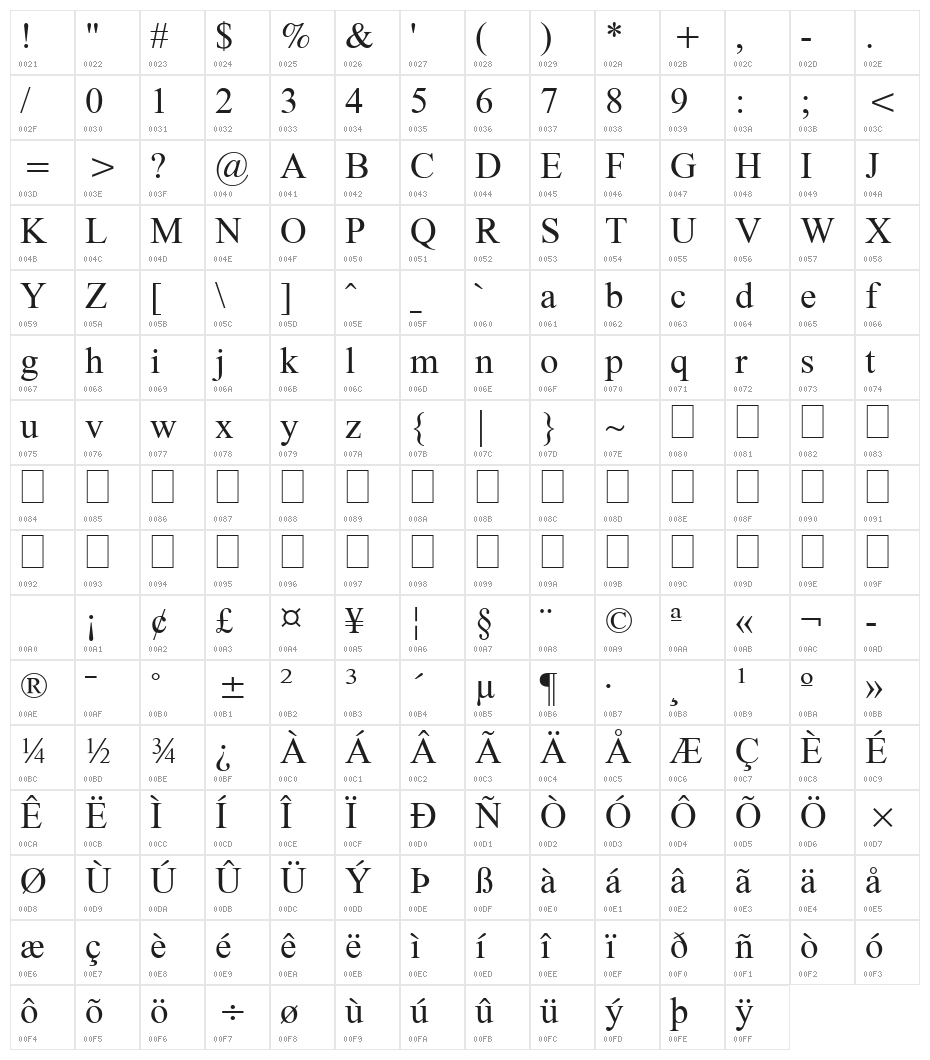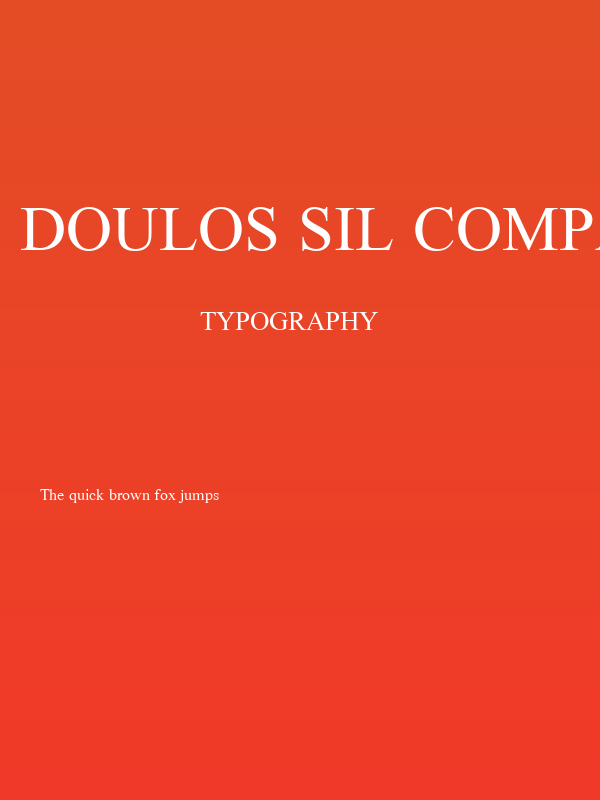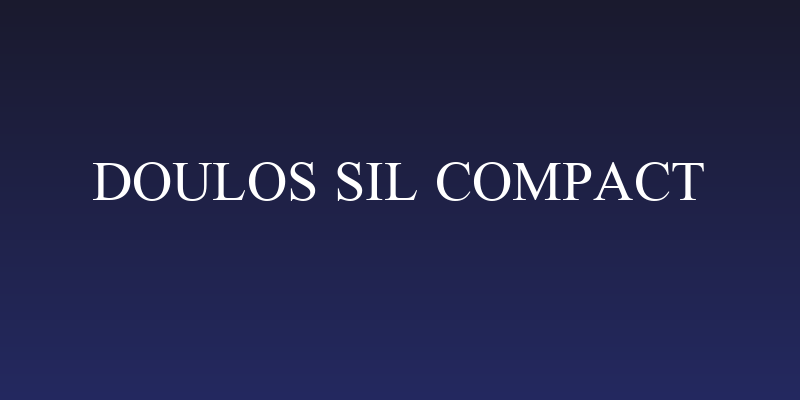
Doulos SIL Compact Font
| Nome | Doulos SIL Compact |
| Categorie | Serif |
| Caso d'uso | Body text, Headlines, Formal documents |
| Progetti proposti | Ideal for projects requiring a traditional and professional look, such as book typesetting, formal invitations, academic papers, and corporate branding. |